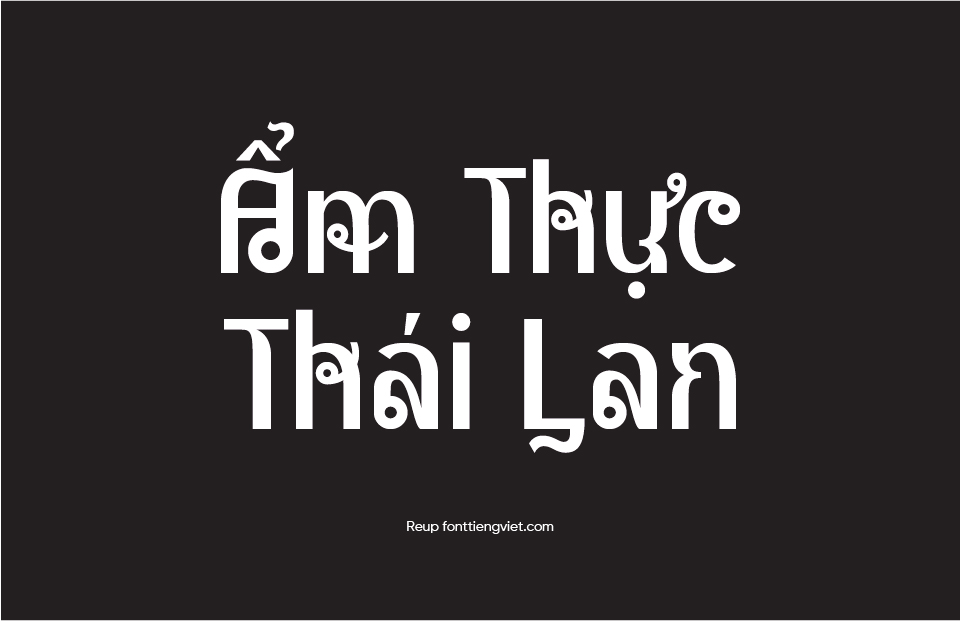
Font Việt hóa SVN Nakhon Kanlaya
Giới thiệu về bộ Font Việt hóa SVN Nakhon Kanlaya
Trong thế giới đồ họa hiện đại, việc tìm kiếm một bộ Font Miễn Phí chất lượng luôn là ưu tiên hàng đầu của các nhà thiết kế. Font Việt hóa SVN Nakhon Kanlaya nổi lên như một lựa chọn hoàn hảo nhờ sự kết hợp tinh tế giữa nét đẹp truyền thống và hơi thở đương đại. Đây là bộ font mang đậm phong cách Thái Lan, được chăm chút kỹ lưỡng về đường nét để phù hợp với bảng mã tiếng Việt, giúp người dùng dễ dàng sử dụng trong nhiều dự án sáng tạo khác nhau mà không lo lỗi hiển thị hay thiếu ký tự đặc biệt.
Những đặc điểm nổi bật của Font Việt hóa SVN Nakhon Kanlaya
Thiết kế độc đáo và linh hoạt
Font Việt hóa SVN Nakhon Kanlaya sở hữu cấu trúc các ký tự mảnh mai nhưng cực kỳ chắc chắn, tạo cảm giác thanh lịch và sang trọng. Điểm đặc biệt của bộ font này chính là sự mềm mại trong các nét uốn lượn, gợi liên tưởng đến các tác phẩm nghệ thuật thủ công. Nhờ vào sự linh hoạt này, các bạn học sinh và giáo viên có thể ứng dụng font vào việc làm báo tường, thiết kế bìa sách hoặc các bài trình chiếu PowerPoint để bài học thêm sinh động và lôi cuốn hơn.
Tính ứng dụng cao trong đời sống
Không chỉ giới hạn trong học đường, bộ font này còn cực kỳ hiệu quả khi dùng cho thiết kế logo, thực đơn quán cà phê hay các thiệp mời sự kiện. Với việc được tối ưu hóa đầy đủ dấu tiếng Việt, người dùng có thể yên tâm sáng tạo nội dung mà vẫn đảm bảo tính thẩm mỹ cao nhất.